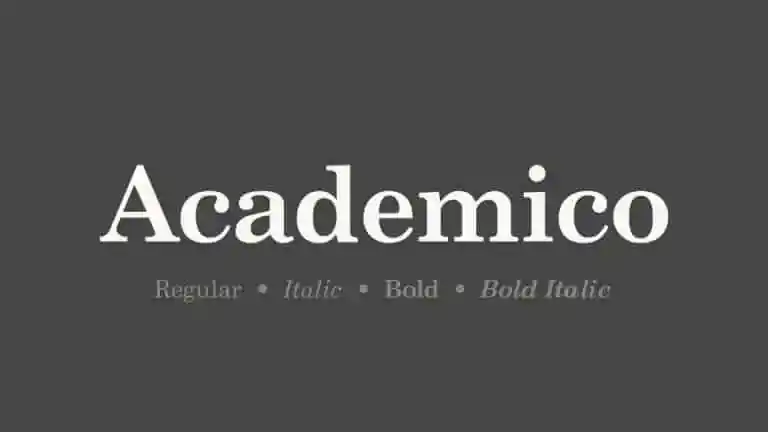
Introduzimos Academico Serif Font, uma fonte serifa com caracteres robustos e fortes baseada no New Century Schoolbook. Esse design é ideal para textos de destaque grande, textos longos, designs de panos e logotipos que exibam um impressiono antigo. Além disso, a Academico Serif Font vem em dois pesos com itálico correspondente. A fonte é especialmente adequada para qualquer projeto que deseje dar ao texto uma aparência antiga e sofisticada, tornando-a perfeita para aplicações que exigem um design elegante e profissional. Se você gosta de um estilo desafiador e moderno, mas ainda quer algo mais tradicional, Academico Serif Font é sem dúvida a escolha certa. Sua versão multi-língue facilitará sua aplicação em projetos globais ou que envolvam diferentes idiomas, aumentando ainda mais seu valor como fonte ideal para uso acadêmico. Seja em uma sala de aula, um documento formal ou até mesmo em materiais educativos digitais, Academico Serif Font oferece o equilíbrio perfeito entre modernidade e elegância que seus projetos podem precisar.